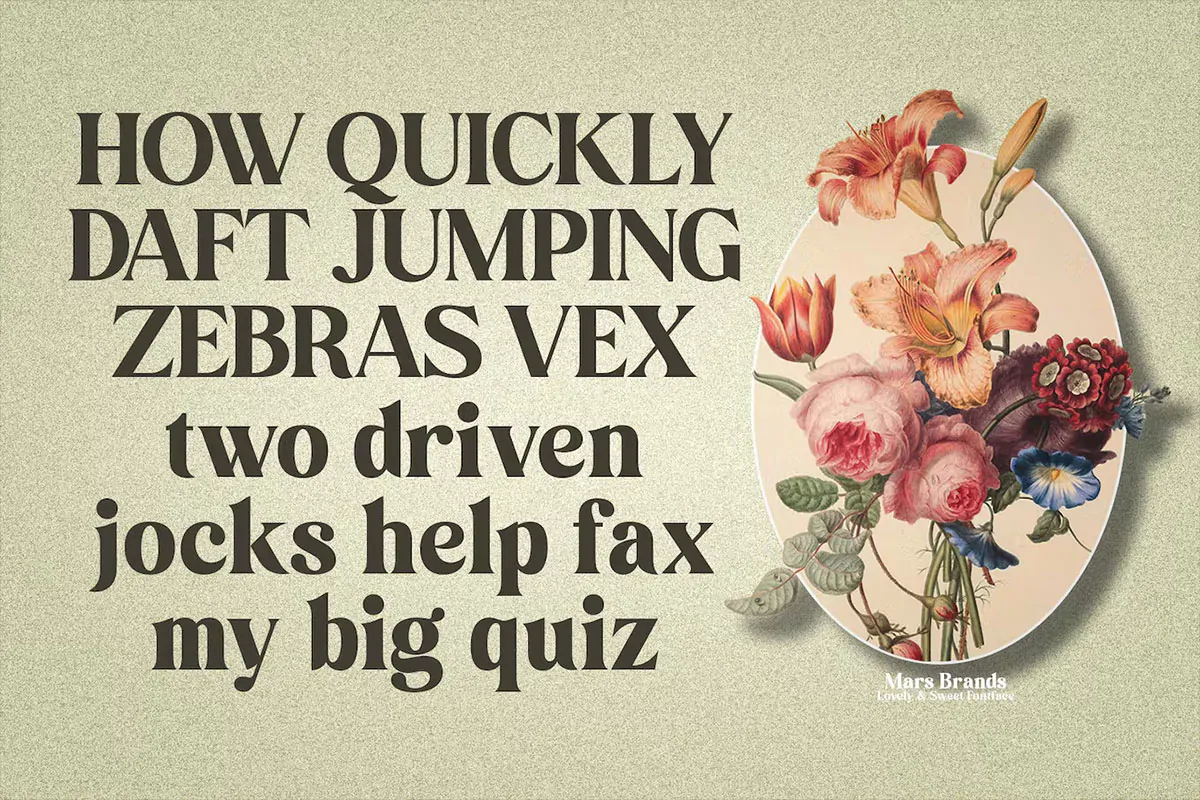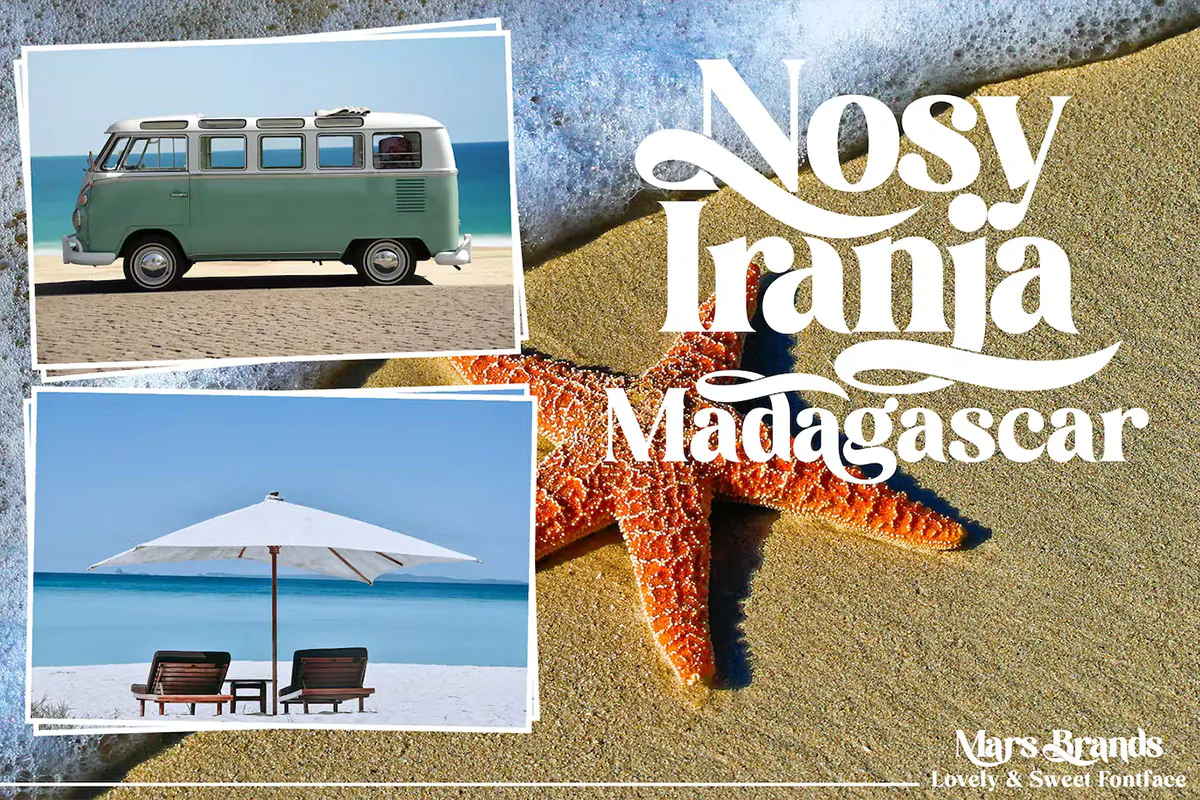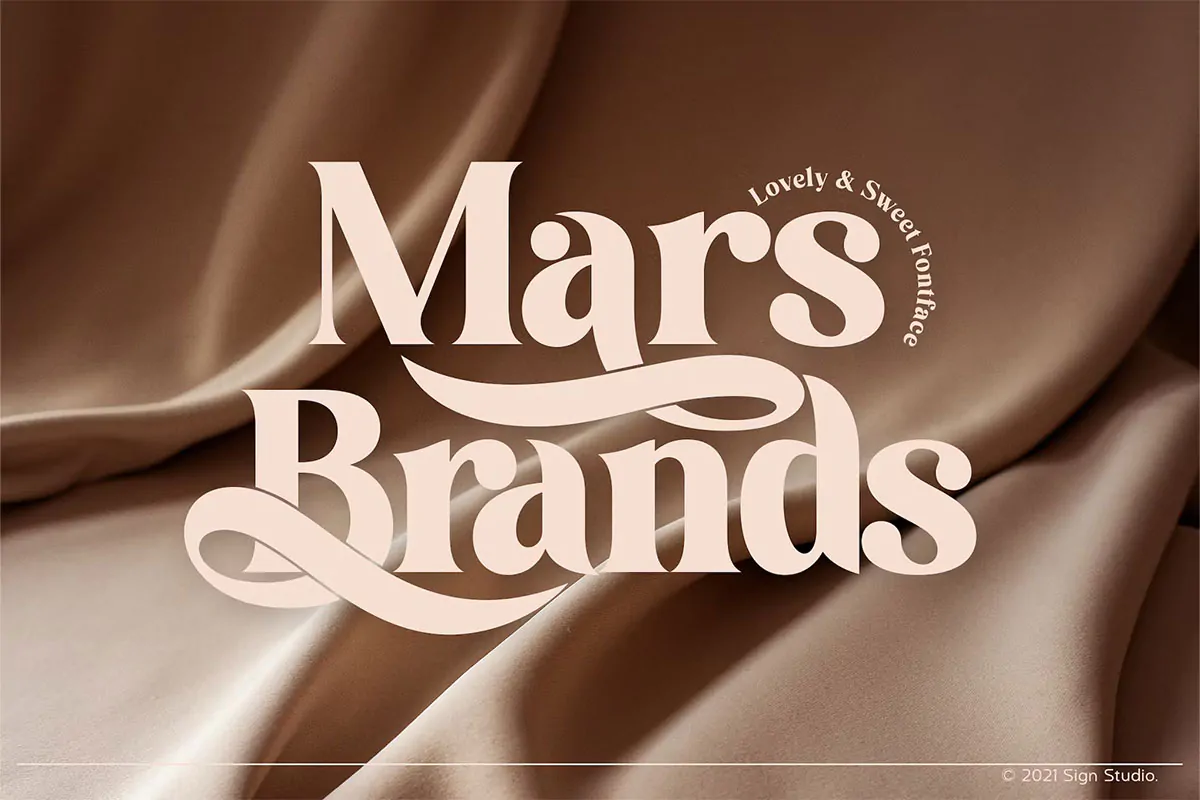
فونت ظریف و زیبای Mars Brand
فونت ظریف و زیبای انگلیسی
فونت ظریف و زیبای Mars Brand یک سریف فونت انگلیسی است که مناسب برای استفاده در طرح و پروژههای گرافیکی مختلف از جمله طراحی پوستر، بروشور، لوگو، کارت ویزیت، بسته بندی محصولات و … میباشد.